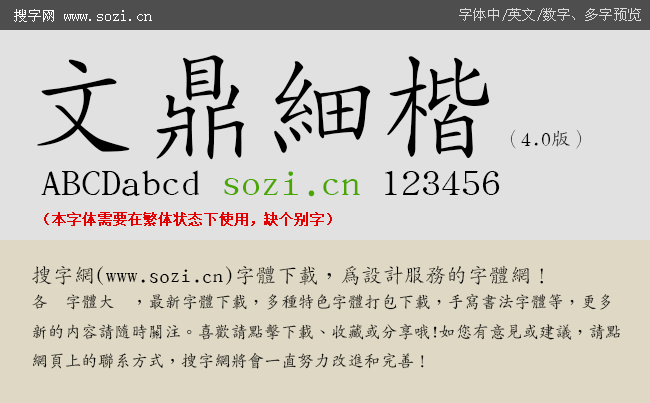
文鼎細(xì)楷
搜字網(wǎng)提供文鼎細(xì)楷中文字體下載,文鼎細(xì)楷是一款字形端正的楷體字,筆畫(huà)看上去比較精簡(jiǎn),筆畫(huà)挺秀均勻,字形端正,可以應(yīng)用于廣告設(shè)計(jì)、名片設(shè)計(jì)、包裝印刷、產(chǎn)品設(shè)計(jì)等應(yīng)用。